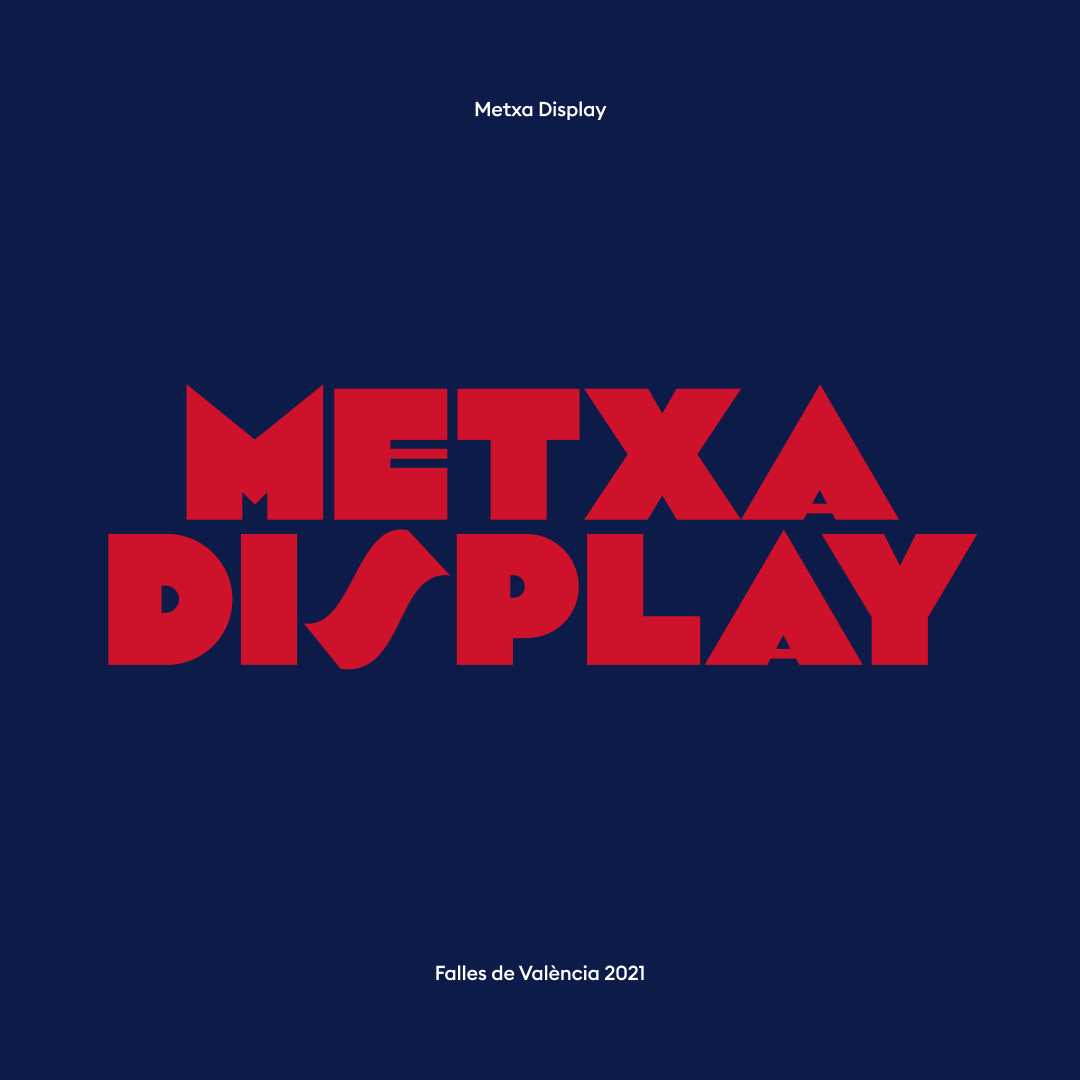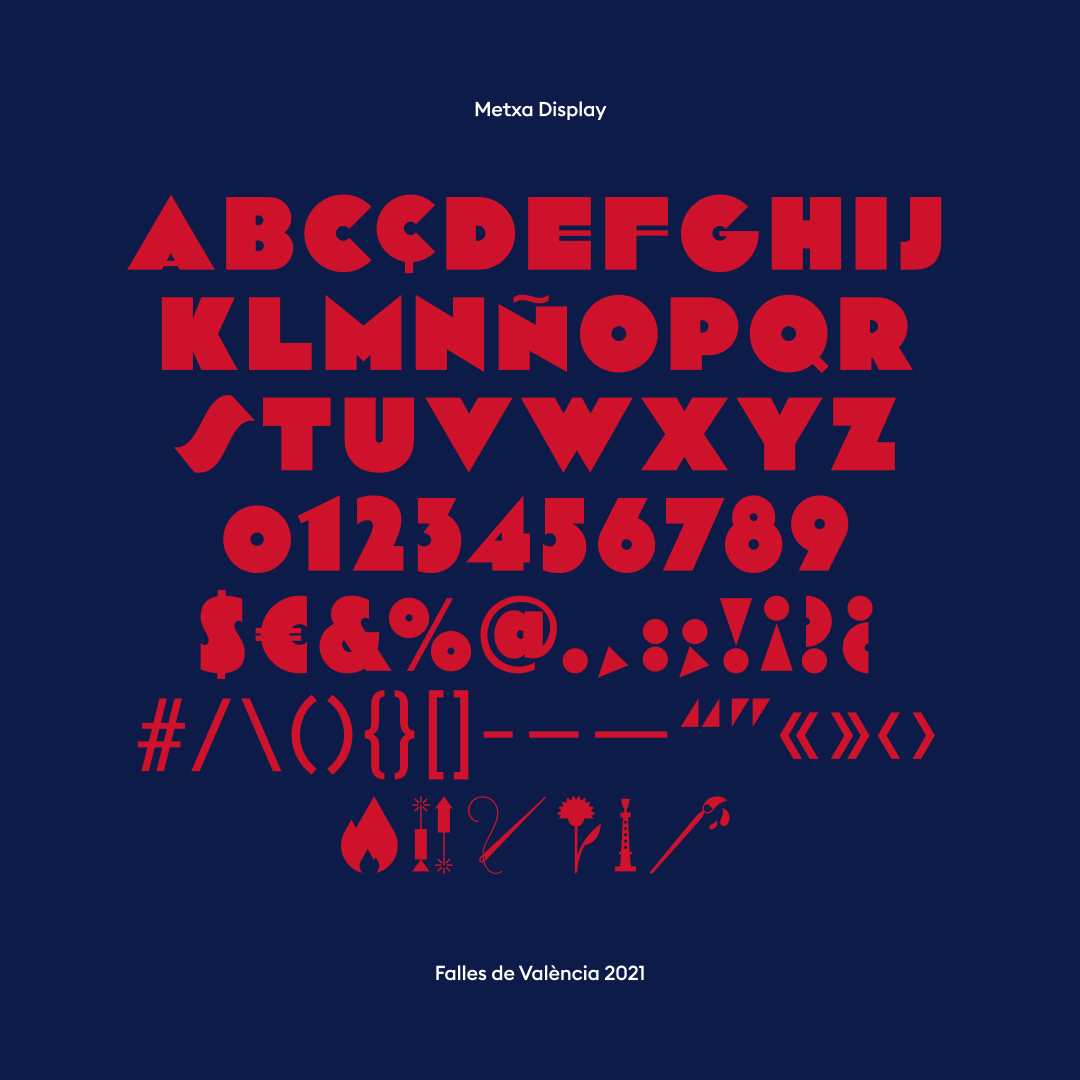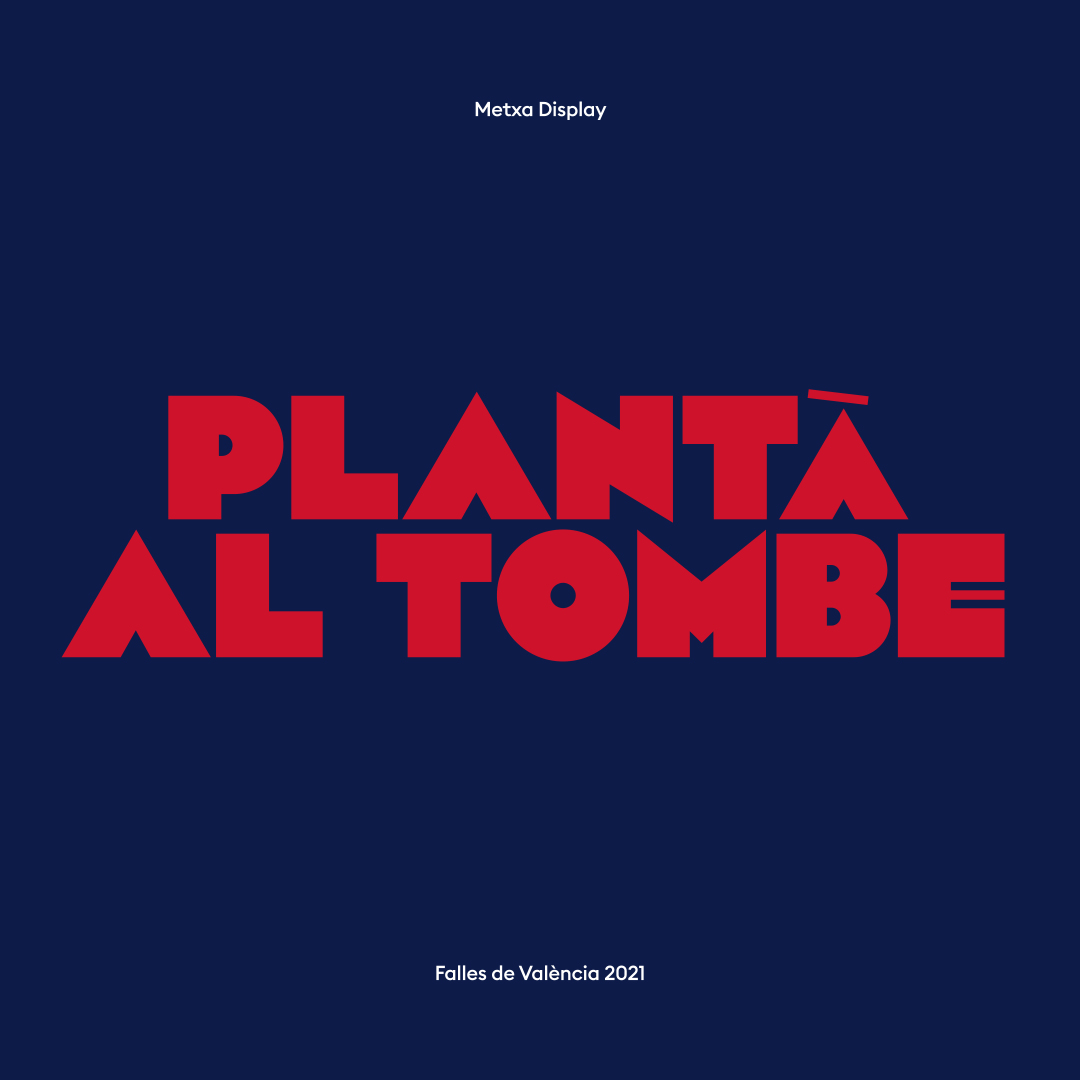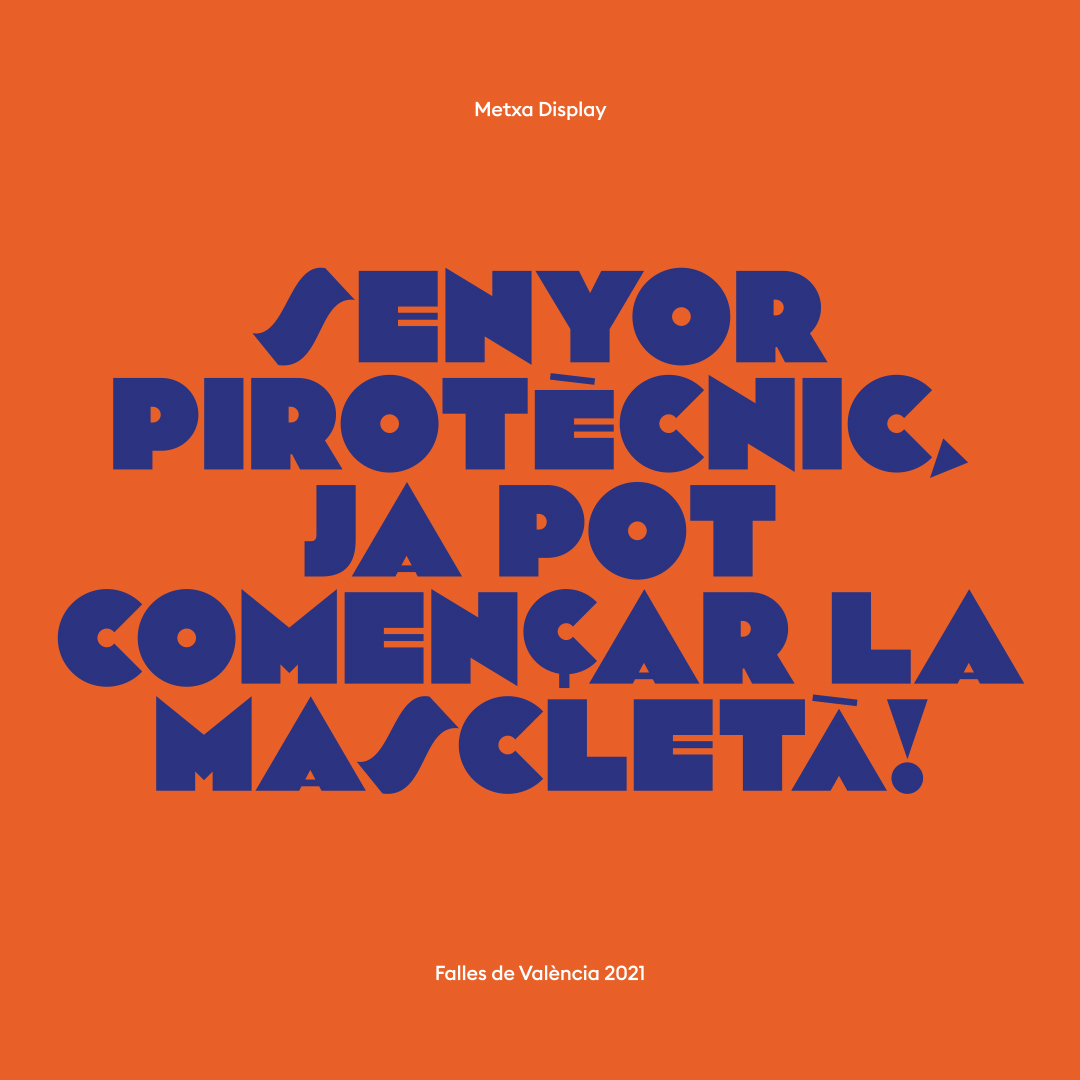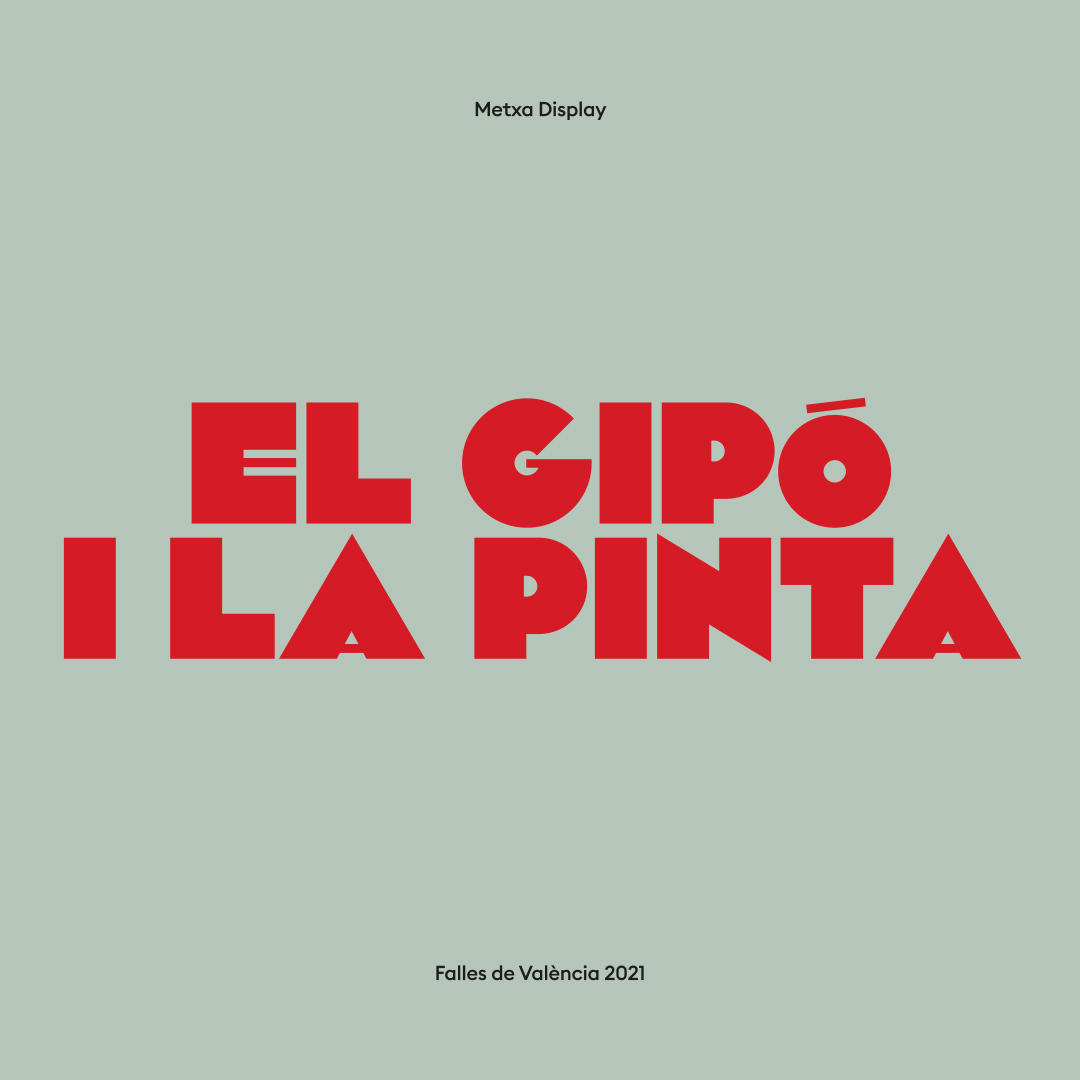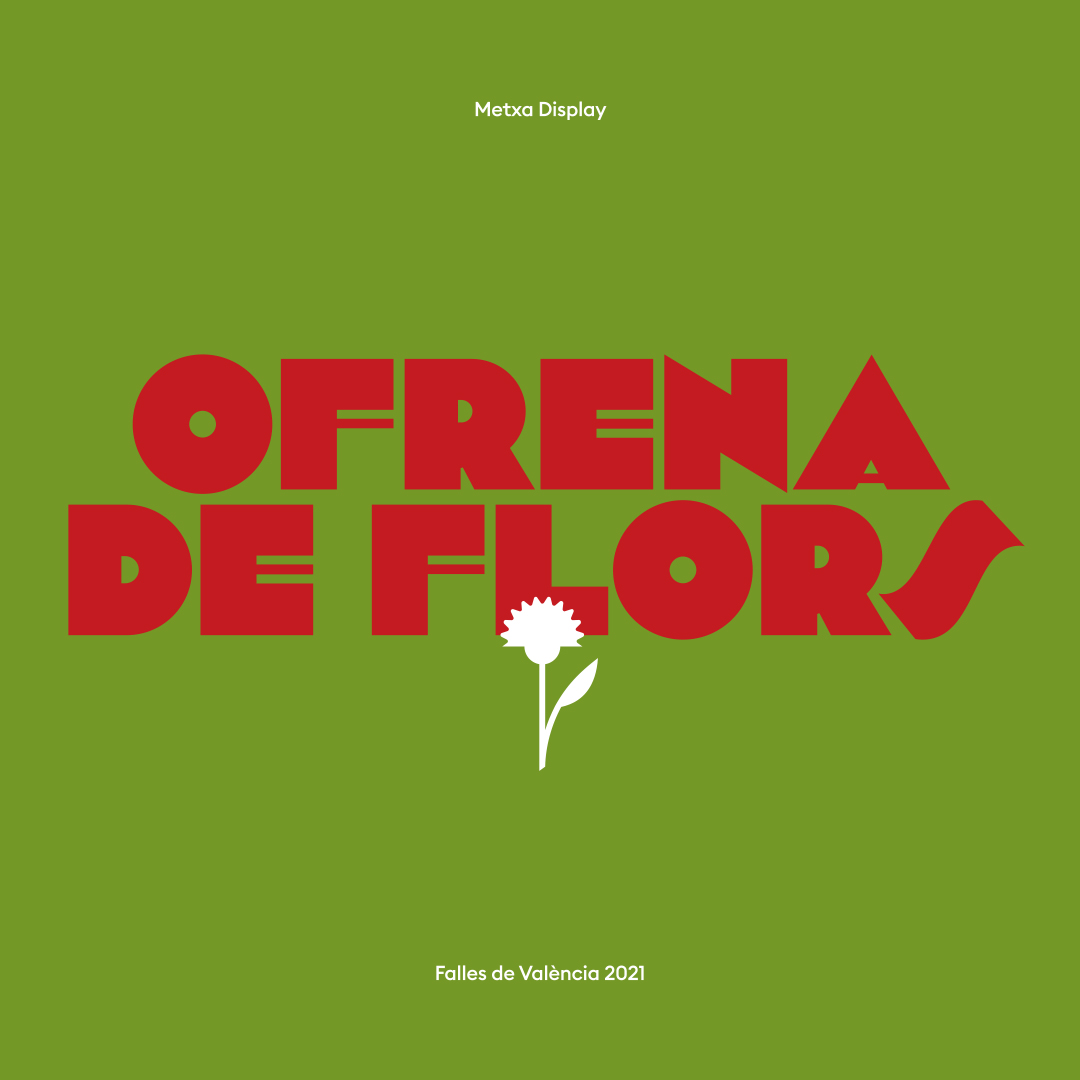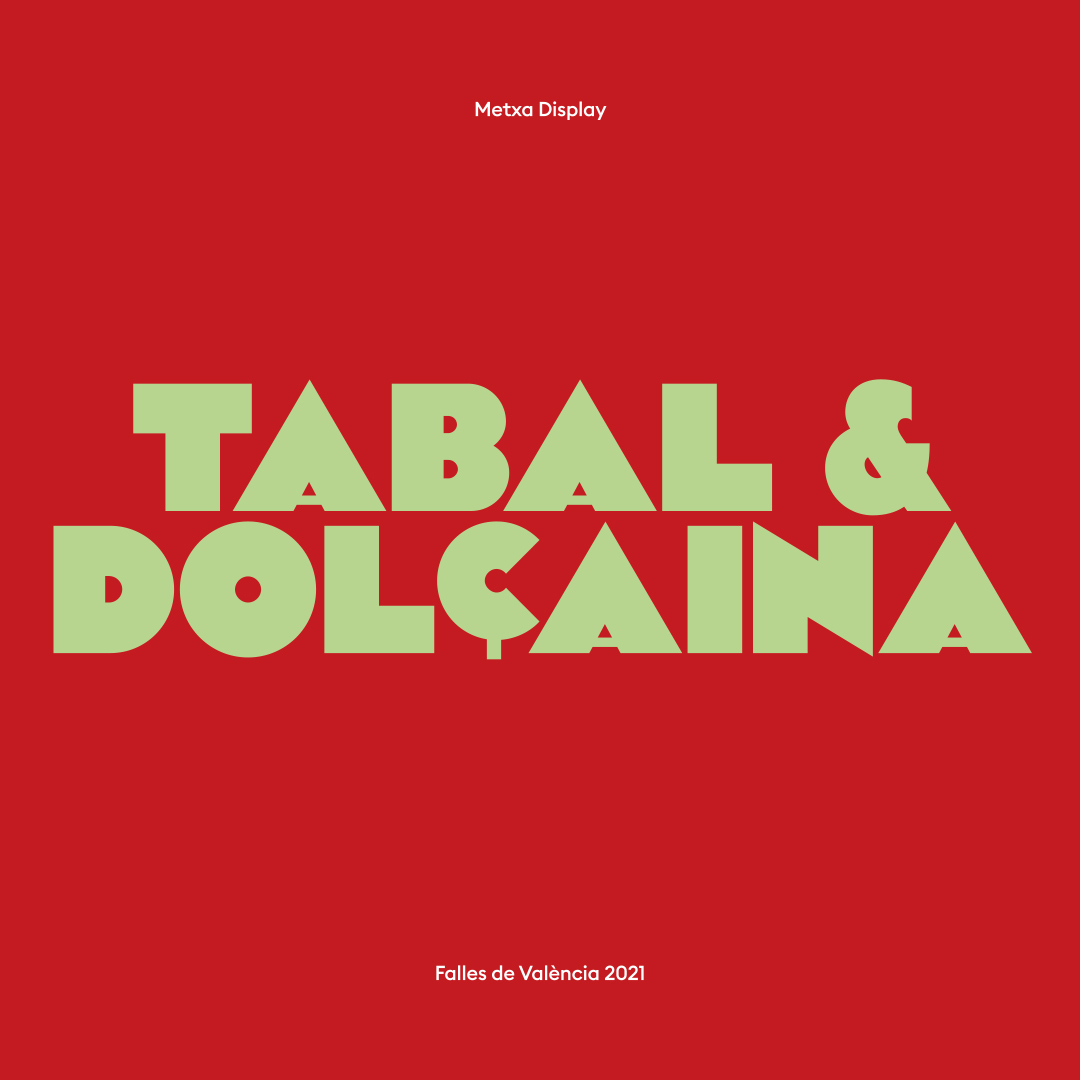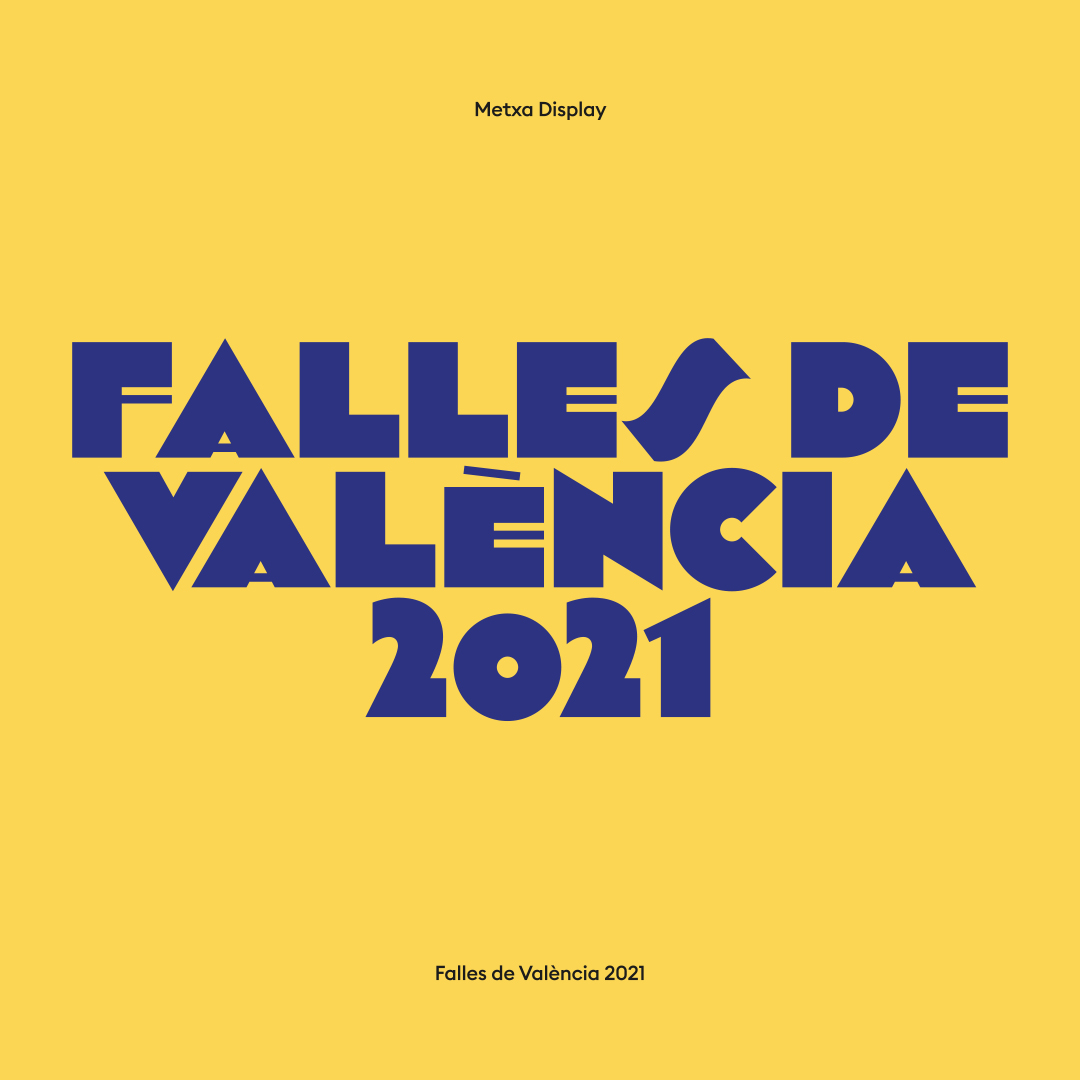
Fase Studio pone a disposición de los usuarios la tipografía Metxa Display, creadas para las Fallas 2021.
Influencia del art decó
La campaña gráfica de Fallas 2021, creada por Diego Mir y Fase Studio, es un homenaje a los oficios que hacen la fiesta posible: un reconocimiento y una reivindicación de las raíces. A nivel formal, la campaña es también un homenaje a la tradición gráfica. Uno de los elementos gráficos que se emplean es «Metxa», una tipografía de estilo art decó creada por el estudio valenciano Fase Studio. «Metxa» es una tipografía para titulares, es decir, que está diseñada para utilizarla en frases cortas o conjuntos de pocas palabras, y en tamaños grandes.
Esta tipología en concreto, se repite con frecuencia en la primera época de los carteles de fallas, así como en muchas piezas gráficas de aquellos años en València. Aún así, para elaborarla se han recogido influencias de este estilo de toda Europa, en especial de Italia, Francia y España.
Características de «Metxa»
La tipografía se concibe sólo con caja alta y especialmente diseñada para comprimir mucho en interlineado, pues se reducen las formas para dar cabida a los signos diacríticos, entre otros. Tiene dos opciones de «A» para tamaños reducidos, aunque se recomienda no aplicarla en tamaños menores de 30 pt. La tipografía se ha desarrollado de la misma forma que lo hicieron los cartelistas de aquella época, como un juego en el que prima la forma geométrica sobre los conceptos ortodoxos del diseño tipográfico.
Esta primera versión, que se encuentra en fase beta, ha sido diseñada por Fase Studio (Cristina Alonso y Raül Vicent) e incluye unos dingbats falleros dibujados por Diego Mir. Se puede descargar desde la web de fallas.com y es de uso libre y gratuito.